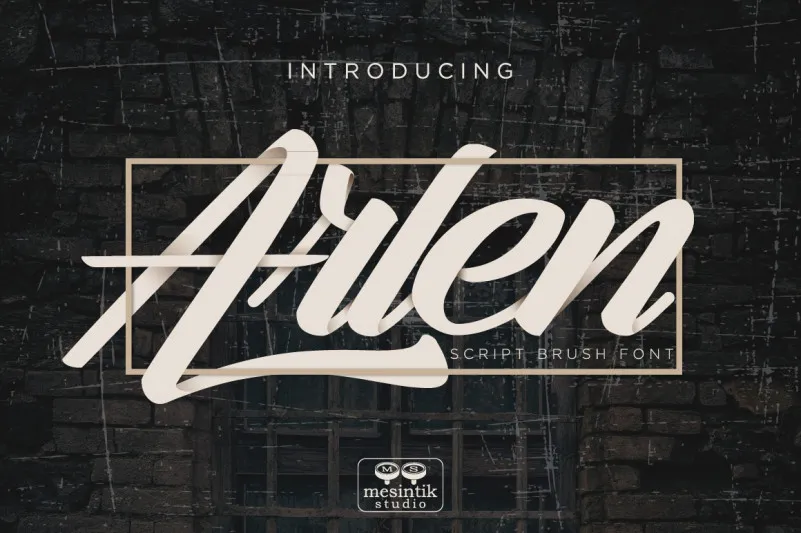
A Arlen Script é uma tipografia script de esmalte que oferece um equilíbrio elegante entre a simplicidade e o charme. Ideal para aplicar em capas de livros, logotipos, assinaturas, designs de casamentos, embalagens de produtos especiais e diversos eventos importantes. Esta fonte é uma excelente escolha tanto para designers gráficos quanto para pessoas que buscam um visual atraente para seus trabalhos digitais. A Arlen Script não só traz vida à sua arte digital, mas também adiciona um toque único ao seu design final. Se você está procurando por uma fonte de esmalte que ofereça uma variedade de opções elegantes e modernas, a Arlen Script é perfeita para incorporar em projetos diversos. Suas linhas fluidas e sutis permitem criar letras delicadas ou robustas dependendo da aplicação desejada. Seja para um projeto de marca, um logotipo criativo ou mesmo para escrever uma carta de casamento personalizada, a Arlen Script se encaixa perfeitamente no seu estilo e tornará sua arte digital um verdadeiro trunfo.
Designer: Mesinitik Studio